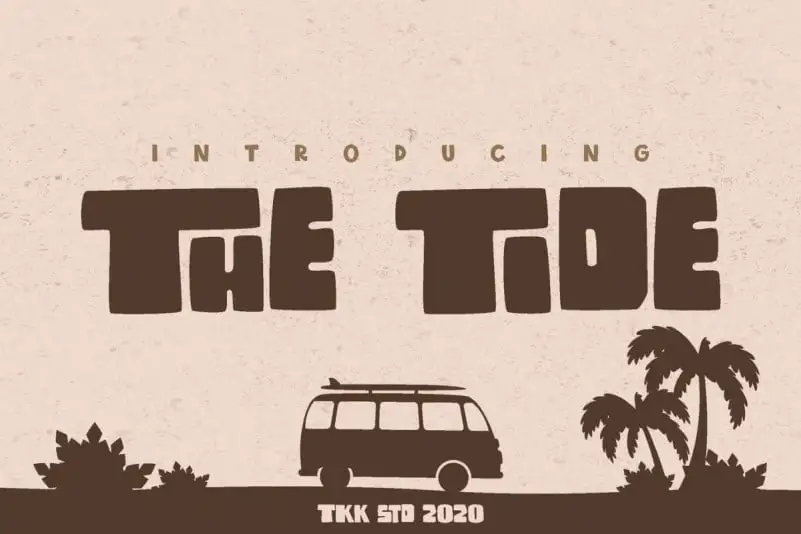
The Tide Display Font – Download Grátis
A fonte The Tide Display Font é uma criação deslumbrante dos anos 2020 do designer 99designs. Com linhas claras e sutis, ela transmite um sentido de descontração e energia rebelde que remete a ondas do mar. O nome da font foi inspirado nas incríveis sensações que vêm ao imaginar um dia de praia quente com um vento sussurrando nos cabelos, uma onda crescente invadindo a orla enquanto o surfista corta furiosamente pela frente. A The Tide é perfeita para seus posters e anúncios criativos que buscam transmitir esse espírito despreocupado e vibrante. Ideal para qualquer projeto visual que busque um toque de brilho e frescor, seja para uma campanha publicitária ou apenas decorar a estação do verão em seu site ou loja online.